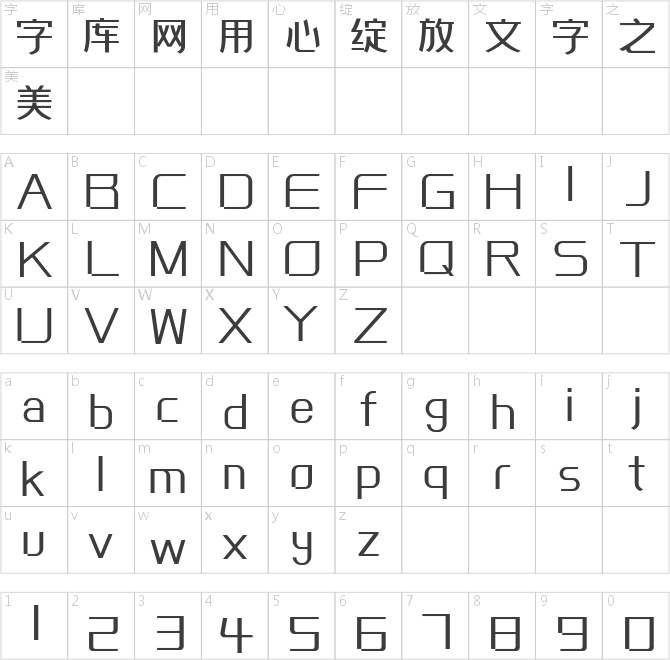
字體名稱: 卓健橄欖簡體
卓健橄欖簡體
卓健橄欖簡體介紹
卓健橄欖簡體是由卓健設計團隊制作,是一款相對較時尚的字體,部分筆畫的斜切處理,也讓字體更具設計感和時尚屬性,整體中心是偏上一點,更符合現代審美。字體圓角設計,讓整個字體更加圓潤,富親和力。口字結構,左下角留白,個性化處理更具特色。字庫共7050個常用字,感謝卓健設計團隊的分享。